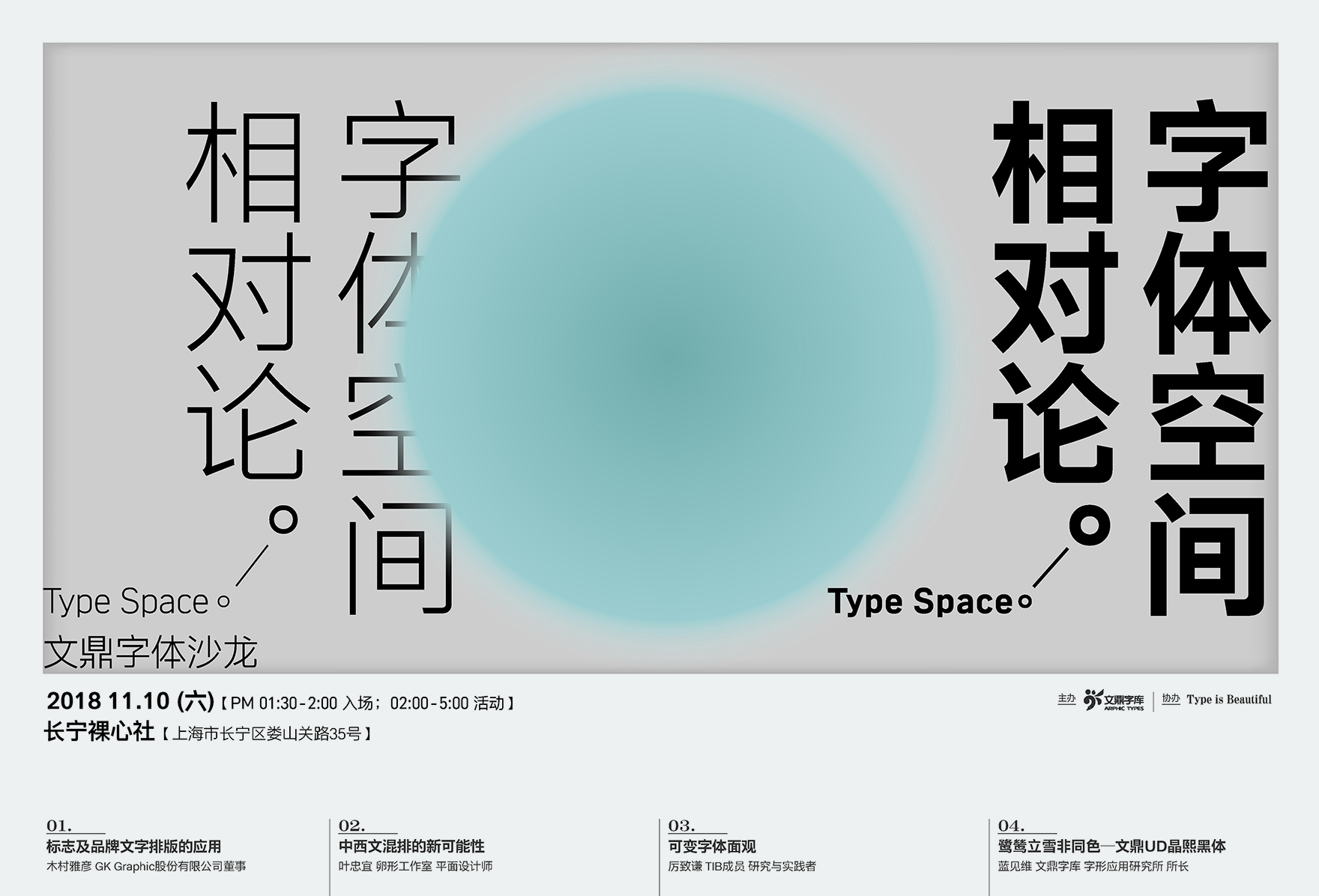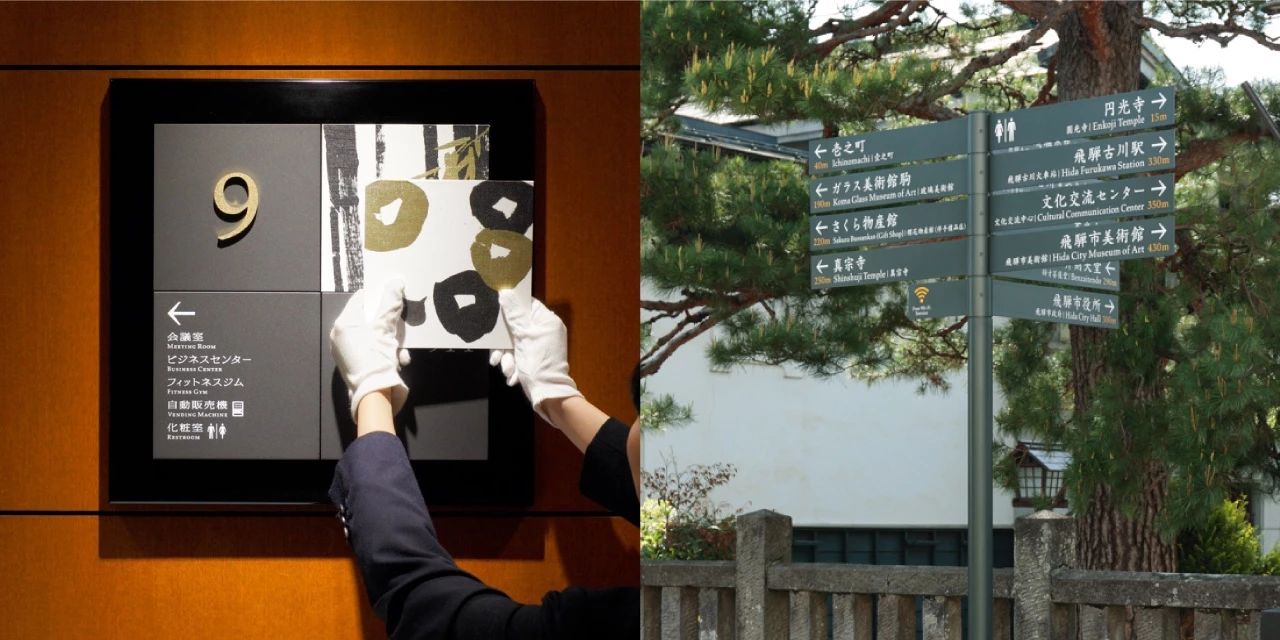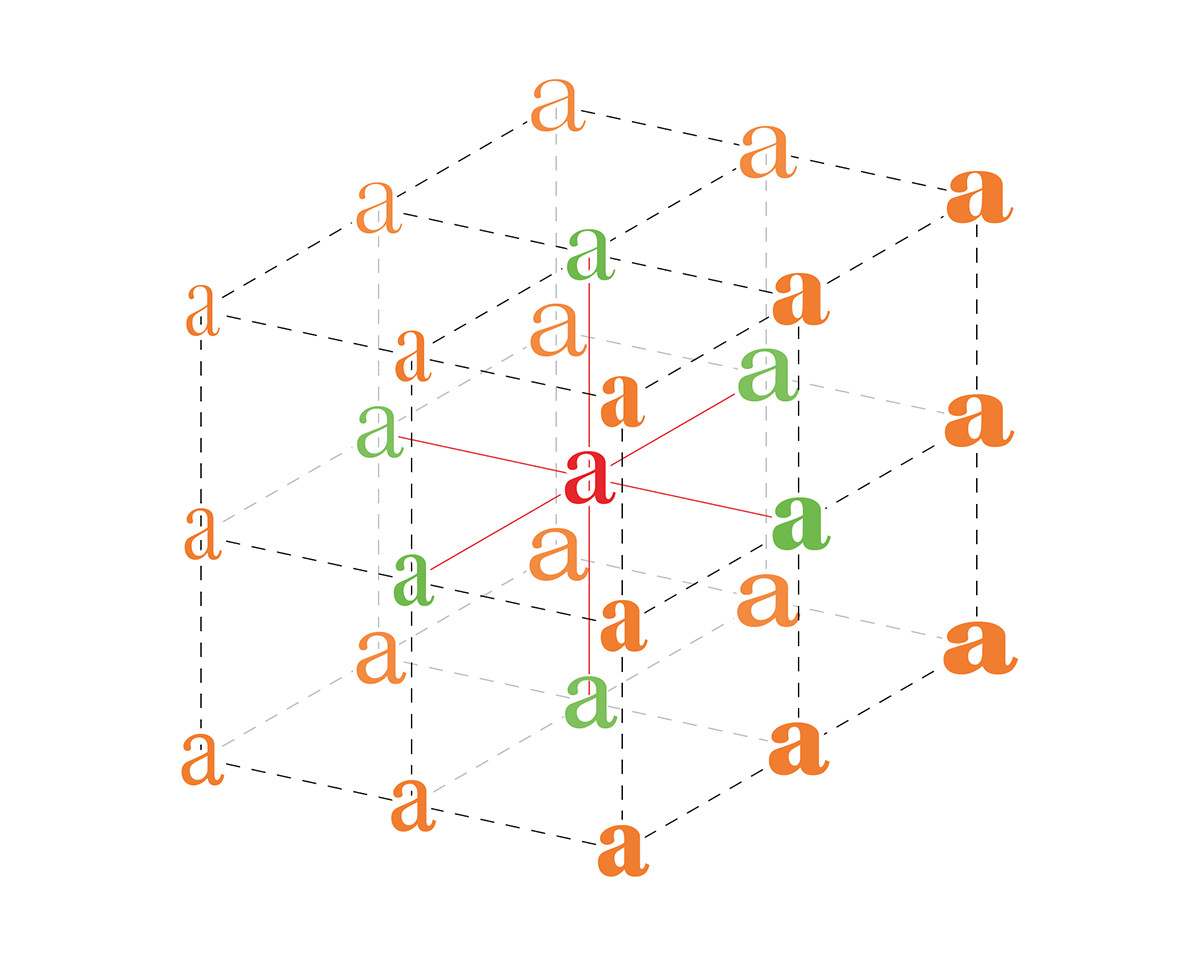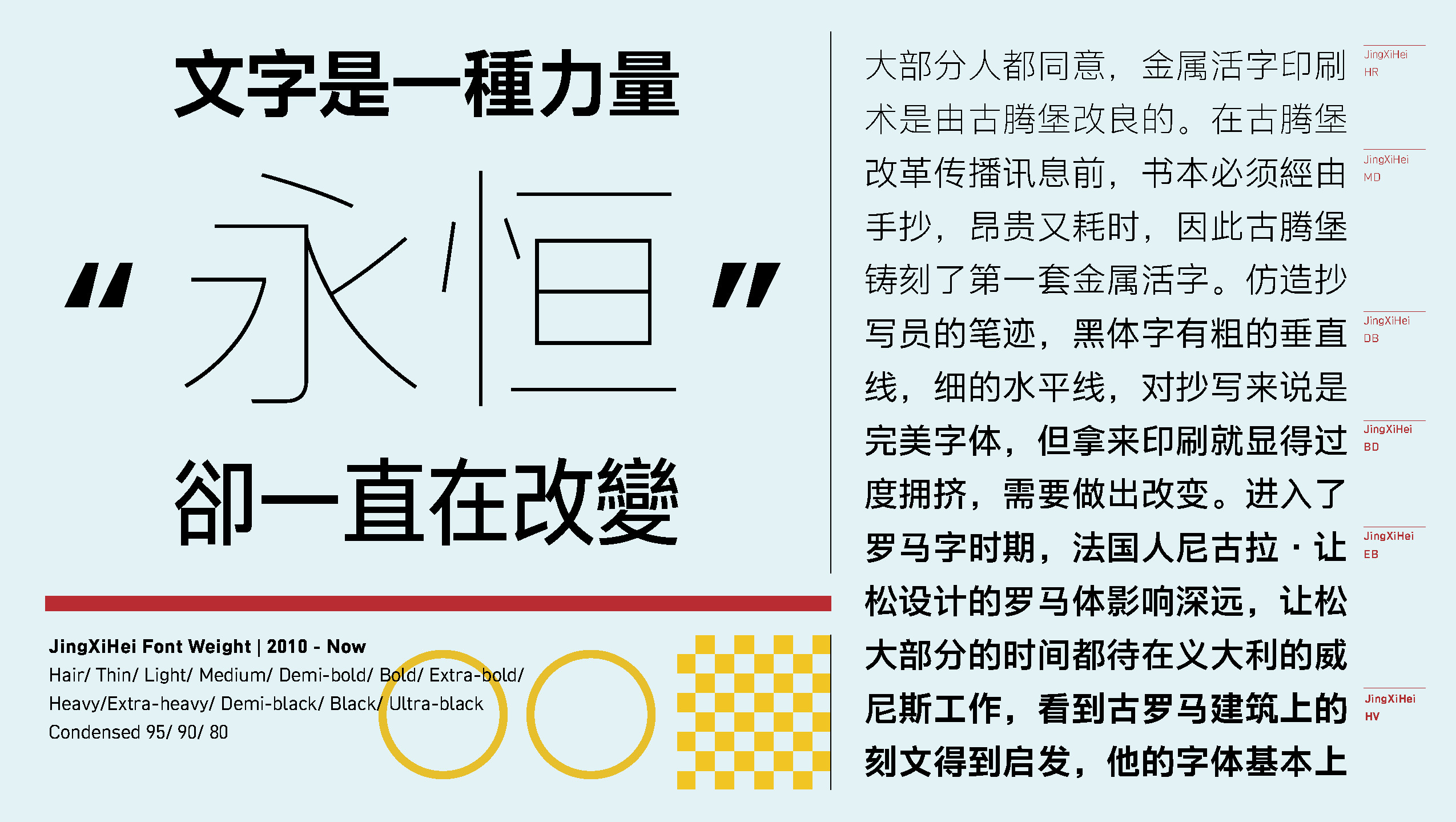
「Type Space | 字体空间相对论」主题沙龙
也许你还记得去年秋天 TIB 在上海协办的「TypeTime! 文鼎字体设计沙龙及多媒体展览」,呈现字体开发的今昔之比、讨论字体作为品牌要素的力量、畅想字体技术的未来。今年,我们将目光从时间转向了空间。
文字所处的空间,为字体的设计、选择与运用带来了多大的可能性?——公共场所、实体纸页、数字屏幕、甚至虚拟映像……环境条件的差异与变化,对字体应用提出了多样化的要求,对字体的选择也无法停留于简单孤立的风格判断,而是与空间中其他元素相呼应、互动的复杂决策。
因此,不管是平面设计师、建筑/室内设计师、交互设计师、开发者,还是空间体验的策划者、管理者,都会在各自的工作中遇到文字设计如何匹配环境的问题。那么应当综合考虑哪些因素?怎样判断和决策?最新的字体技术又为各种应用场景提供了怎样的便利?在「Type Space | 字体空间相对论」主题沙龙中,来自东京、台北、上海的设计师将与大家分享和探讨这些问题。
Type Space | 字体空间相对论
文鼎字体沙龙
演讲嘉宾
• 木村雅彦,日本 GK Graphics 股份有限公司董事
• 叶忠宜,平面设计师,台北卵形工作室主理人
• 厉致谦,Type is Beautiful 成员,多领域设计者与研究者
• 蓝见维,文鼎字库字体应用研究所所长
主持、日文翻译
Eric Liu(刘庆),Type is Beautiful 编辑,「字谈字畅」主播
沙龙内容
01 标识及品牌文字排版的应用
在公共环境中,文字的易读性,信息的传达力,是至关重要的课题。但现实中,市场取向往往偏好新奇的风格,或者对潮流技术趋之若鹜,最核心的功能可能反倒不受重视。
城市空间是广泛而多层级的,人群与标识物之间的关系也是流动的,这就要求对信息的层级做仔细的统筹判断,并借由文字和视觉有效地予以传达。木村雅彦先生将分享日本 GK Graphics 在交通系统文字开发过程中的基础研究,探讨文字标识如何履行信息传达和环境视觉提升的功能。
02 中西文混排的新可能性
文字排版在应用上是微观的,思考上却是宏观的。文化的多元发展带来了语料的丰富性,多文字在平面空间中有多种并存的可能性,它们在空间中与彼此的关系其实可以交融出更多新的说话方式。
从铅字时代到照排时代,再至今日的数码时代,文字设计的门槛随着科技的演进逐渐降低,也有了更多探索的空间。在这之中,叶忠宜开始对于中西文的混排有了一些趣味的想像:有人说日文排版因汉字与假名之间的形态差异而显得疏密有致、节律如行云流水;那么西文之于汉字的对应关系,又可以怎样看待呢?
03 可变字体面面观
数字技术的发展以及终端设备的多样化,使文字信息所处的空间变得越来越复杂和不稳定。从不同尺寸和分辨率的设备屏幕、不同规格的网页浏览器、不同制式的文件,到沉浸式的虚拟与增强现实环境……时刻变化的多媒介空间,要求字体设计和应用具有高度的灵活性。OpenType 字体格式对可变字体的支持,就在这方面创造了更多的可能。
TIB 作为关注文字设计与视觉文化的综合性媒体,也曾在 OpenType 可变字体规范发布的第一时间,回顾了整个参数化设计概念的历史发展。在本次沙龙的现场,我们则将从实际操作的角度,向大家展示可变字体的技术原理、演示效果,并且展望分析这一技术的应用前景与挑战。
04 鹭鸶立雪非同色——文鼎 UD 晶熙黑
文字设计之于空间环境,固然有诸多可能,但若没有基础的字体设计支撑,一切都是无米之炊。如何满足设计师的使用需求,以及如何让文字在空间、媒介中呈现出最佳效果,是字体设计的重要考量。
本次沙龙的主办方文鼎字库将以 UD 晶熙黑的各版本产品为例,对其延伸出的多样化字体家族进行分析,借由不同应用案例与实验的分享,让设计师了解字体产品的特性是如何针对使用情境来开发的,从而在策划和设计作品的同时,对如何选择字体有更明确的衡量标准。